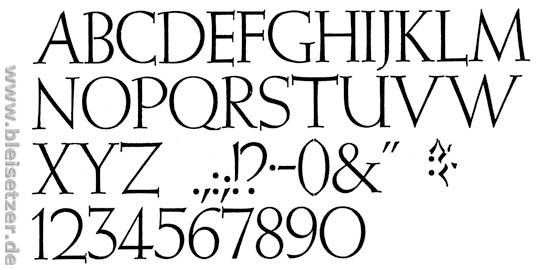
gibt es die Weiß Kapitale als Font zu erwerben?
Falls ja, wo?
myfonts.com kennt sie jedenfalls nicht, da wirst Du schlechte Karten haben. Wenn – wie im Nachbarthread – Geld keine Rolle spielt, frag’ doch mal fontshop, ob sie sie Dir eben schnell mal digitalisieren. :wink:
ich glaube, da fahre ich besser, wenn ich mir einen Andruck mache und den scanne :-)
Ich möchte mal ausprobieren, wie
Preußisches Bleisatz-Magazin aus diesen Kapitalen aussieht.
Wobei es da ein Problem mit dem 'ß' gibt.
sag es ihm.
Korinthe ist Korinthe.
Aber die Weiß Kapitale hat mit der Weiß-Lapidar soviel zu tun wie Korinthen und Erdbeeren.
Du sagst ja auch nicht Tannenberg und meinst die Lithographia.
Und was mache ich dann mit dem "ß"?
Ein SS
Ein SZ
Oder was?
Ich liebe das "ß"
Ein echter Konflikt.
Ihr könntet mir ja ein Versal-ß schnitzen?
So eins? (ganz schnell, ganz schlecht)
Soifz..
Ich muß nachdenken.
In der ganz alten Zeit schrieb man PREUSZEN.
Aber das sieht.. eigenartig aus.
Oder ich gehe von der Weiß Kapitale weg. Und gehe in eine konstruierte Grotesk, Futura Buch oder Futura licht. So im Bauhaus-Stil?
Eine sehr schwere Entscheidung.
Vermarktungstechnisch ist die Koch-Fraktur optimal, weil sie polarisiert.
Das, was durch einen Hausschrift-Wechsel ( :D ) an Polarisierung wegfällt, müßte durch einen anderen entsprechenden Reiz ersetzt werden.
Die Bauhaus ist mir aus Preußen-Sicht zu nahe an den 20er, 30er Jahren.
Es könnte sein, daß sich die intuitiven Assoziationen als eher kontra-produktiv im Marketing-Sinne erweisen.
Was sagt denn die typographische Fachkollegschaft dazu?
Versalien oder gemischt?
Buch oder mager?
Die magere ist wunderschön. Aber in der Versal-Zeile sieht das Versal-R nicht gut aus, oder? In der Buch wirkt es ganz anders.